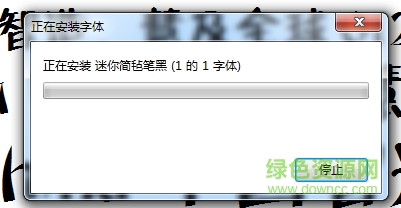
迷你簡(jiǎn)氈筆黑是一款非常有個(gè)性的簡(jiǎn)體字體,這款字的外觀簡(jiǎn)約清新,給人一種脆利落之感,而且落筆非常的有力氣,給人感覺(jué)很不錯(cuò),適合自己使用,有需要的朋友們趕緊來(lái)綠色資源網(wǎng)站下載吧!
迷你簡(jiǎn)氈筆黑是迷你字庫(kù)中最出色的一款簡(jiǎn)體中文漢字,該字體端正大方,效果出眾,并且結(jié)構(gòu)清晰,風(fēng)格統(tǒng)一,可適用于廣告設(shè)計(jì)、平面設(shè)計(jì)、印刷包裝、正文標(biāo)題等領(lǐng)域、